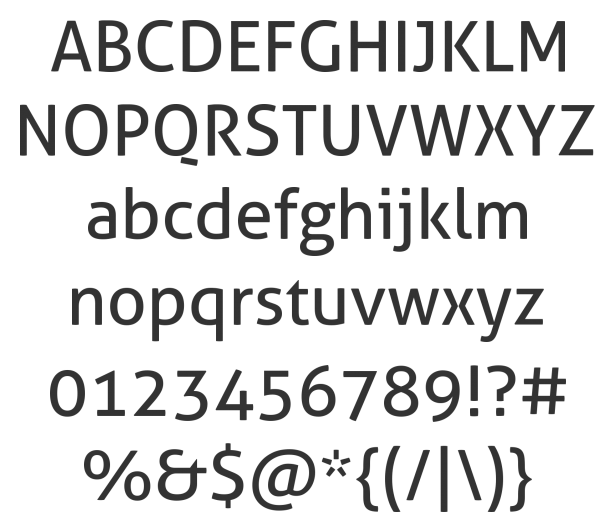
lizenzfreie Brotschrift für Print und Web
ich bin auf der Suche nach einer kostenlosen Schrift für Fließtexte, die sich für Print und Web eignet und zur Aller Regular passt.
Nee, aber nicht zwei so ähnliche Sans mischen :neenee:*
Wenn’s zur Aller passen soll, würde ich eine Serif mit ähnlichem Formprinzip nehmen: Minion, Crimson oder Vollkorn. Einfach mal hier gucken ...
*Sorry, hatte mich verlesen ...
Vollkorn
Die wollte ich auch vorschlagen, aber nur wegen Vollkornbrotschrift. ;-)
… so ähnliche Sans … wenn’s zur Aller passen soll, würde ich eine Serif mit ähnlichem Formprinzip nehmen …
Dann ist doch PT Serif eine gute Wahl! :lol:
Die Vollkorn und Minion wären mir zur Aller dagegen schon wieder zu sehr »renaissance-verspielt«. ;-)
Die PT Serif passt wirklich gut, aber hat jemand vielleicht eine Idee für eine Grotesk?
Abgesehen davon, dass die Aller schon eine Grotesk ist, hat die PT Serif ja noch ein Geschwisterchen namens PT Sans. ;-)
Oh! Da möchte ich gern noch mal auf Schnitzel verweisen. Zwei so ähnliche Sans-Schriften würde ich nicht kombinieren. Das wirkt erstens total unentschieden oder zweitens unprofessionell. So etwas macht immer den Anschein, als ob der Gestalter selbst dachte, es sei beides die gleiche Schrift.
Aber wie Du schon anmerktest: da die Aller ja schon eine (bei den kostenlosen Schriften) recht gute Grotesk ist, stellt sich die Frage, warum man überhaupt noch eine Zweite braucht. Wenn es schon eine Kombination werden soll, würde ich eher zu einer Kontrastschrift raten. Je nach Thema gäbe es da ja auch noch schöne Dipslay-, Script-, etc. Fonts.
Paula, um welches Thema geht es denn bei Deinen Publikationen? Ein paar Hintergrundinfos wären bei dem großen Schriftangebot für weitere Vorschläge sicher zielführender. :-)
Ich brauche eine Brotschrift für ein CI (seriös, modern, offen), bei der die Aller als Hausschrift eingesetzt wird.
Deshalb bieten sich Display- und Script- Fonts hier nicht an.
Was die PT Sans betrifft muss ich dir beipflichten R::bert.
Da die Aller ja sehr gut ausgebaut ist, habe ich auch schon überlegt sie für den Fließtext zu verwenden.
Falls euch dennoch eine Grotesk einfällt, die sich als Brotschrift für Print und Web eignet und mit der Aller harmoniert,
würde ich mich sehr freuen.
... Hausschrift ... als Brotschrift für Print und Web eignet und mit der Aller harmoniert
Warum suchst du eine weitere Grotesk :-?
Die Aller ist ja nicht so besonders und eigenständig als, dass sie nicht als Brotschrift einsetzbar wäre bzw. sich genug von einer anderen Schrift (die ja auch passen und als Brotschrift tauglich sein soll) unterscheiden lässt.